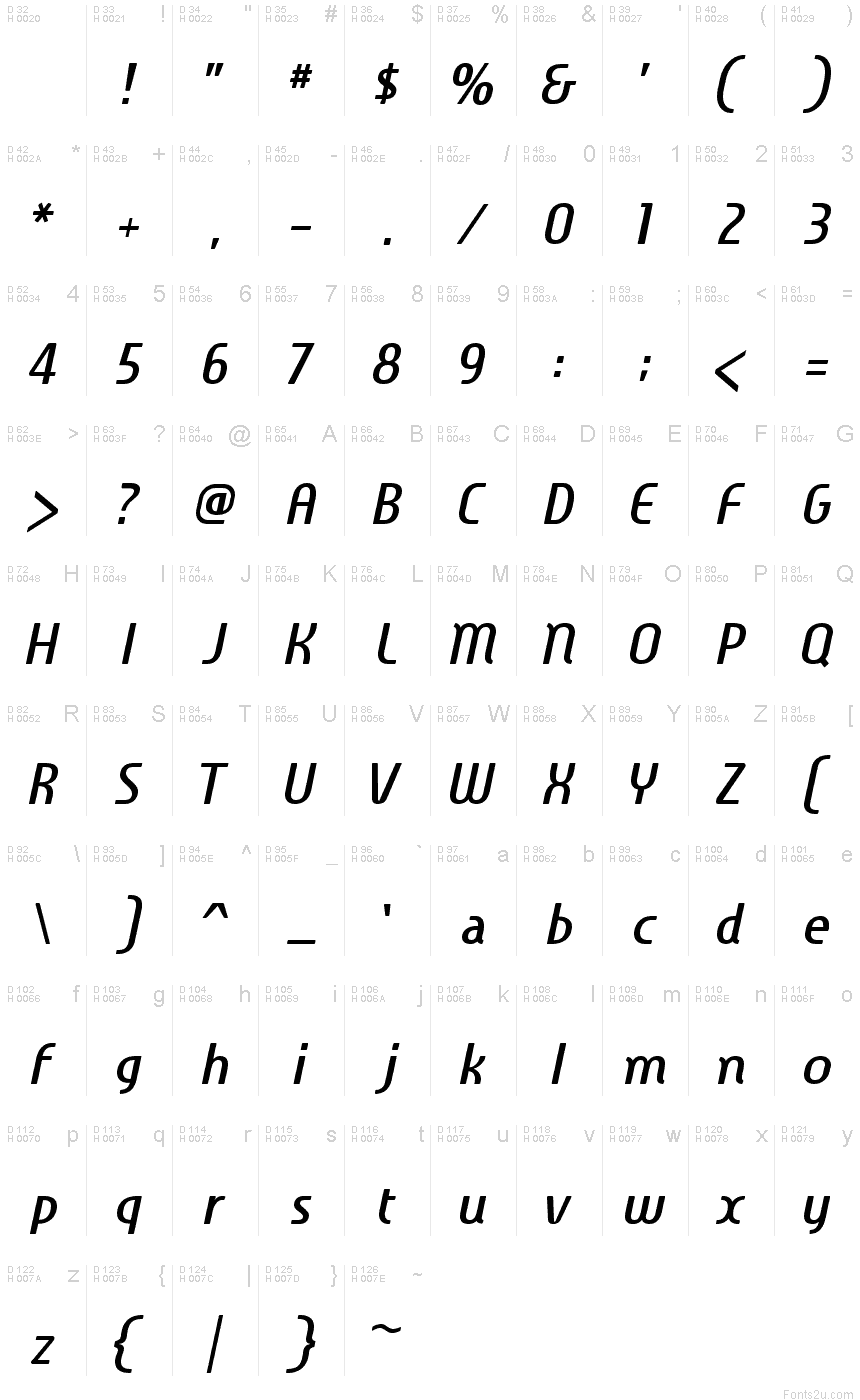
Familian Elder Oblique von Hideki Katayama ist eine moderne, kostenlose Display-Schrift mit einer geschmeidigen Ästhetik, die an Editorial-Designs des späten 20. Jahrhunderts erinnert. Die Buchstaben neigen sich in breiten, fließenden Zügen nach vorne und verbinden weiche Kurven mit stumpfen Enden, was dem Font eine entspannte, aber dennoch formelle Note verleiht.
Sie eignet sich hervorragend für Magazin-Cover, Boutique-Branding, Plakattitel, Verpackungsdesign und Titelkarten – überall dort, wo ein kostenloser Font Bewegung braucht, ohne dabei zu aufdringlich zu wirken. Dank der offenen Kurven und der Neigung ist sie ideal für kurze Zitate und Einschübe, die einen sanften, stilvollen Akzent setzen, statt mit harter Geometrie zu dominieren.